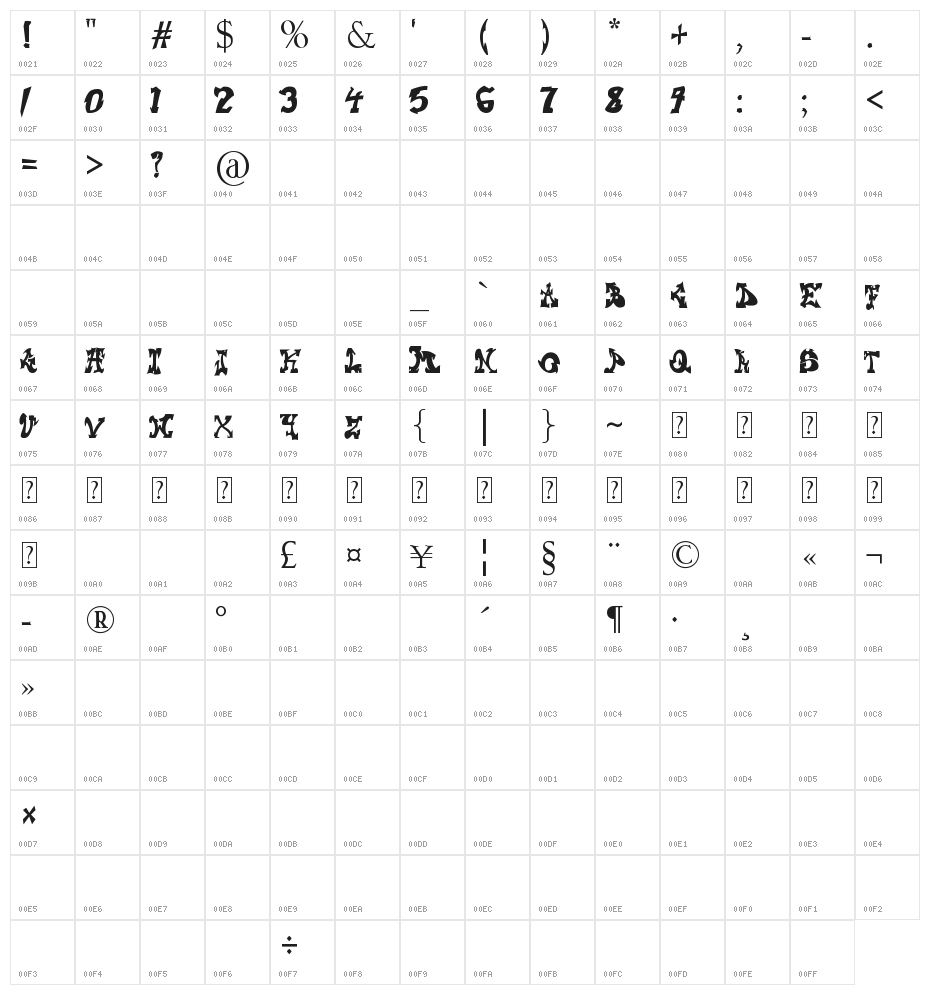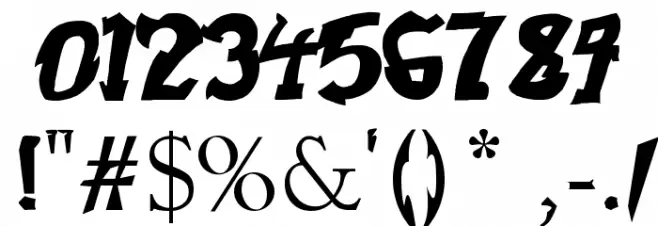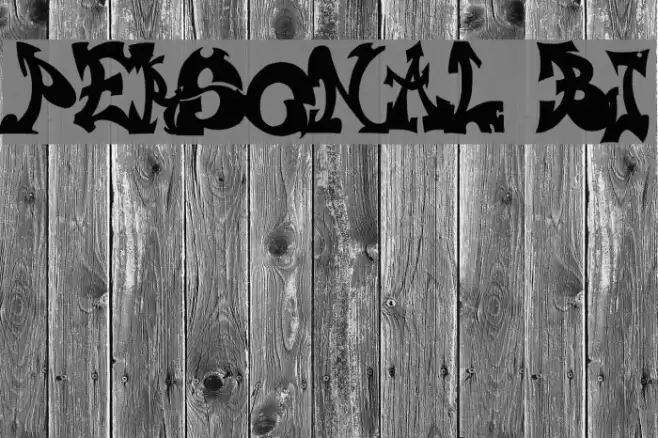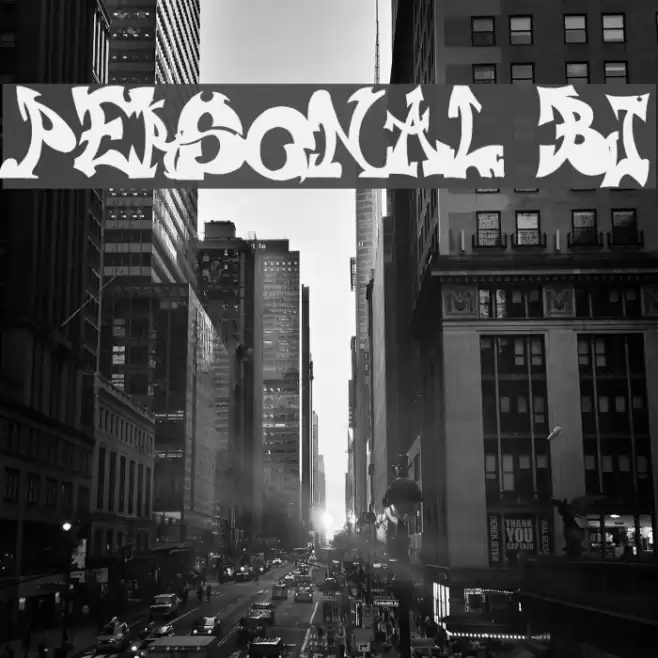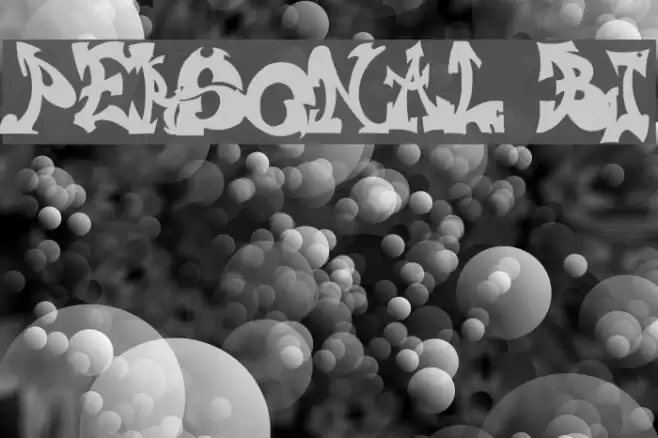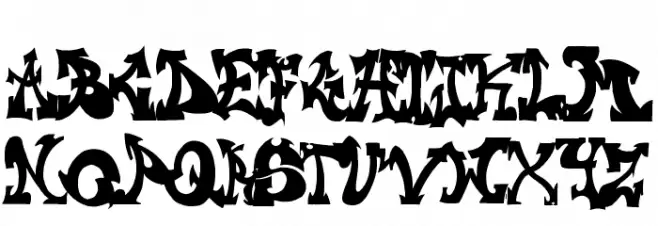
personal bj Font
✎ Graffiti
| مشاريع مقترحة | Ideal for use in graphic design projects that require a bold statement, such as posters, album covers, or branding for edgy or alternative products. |